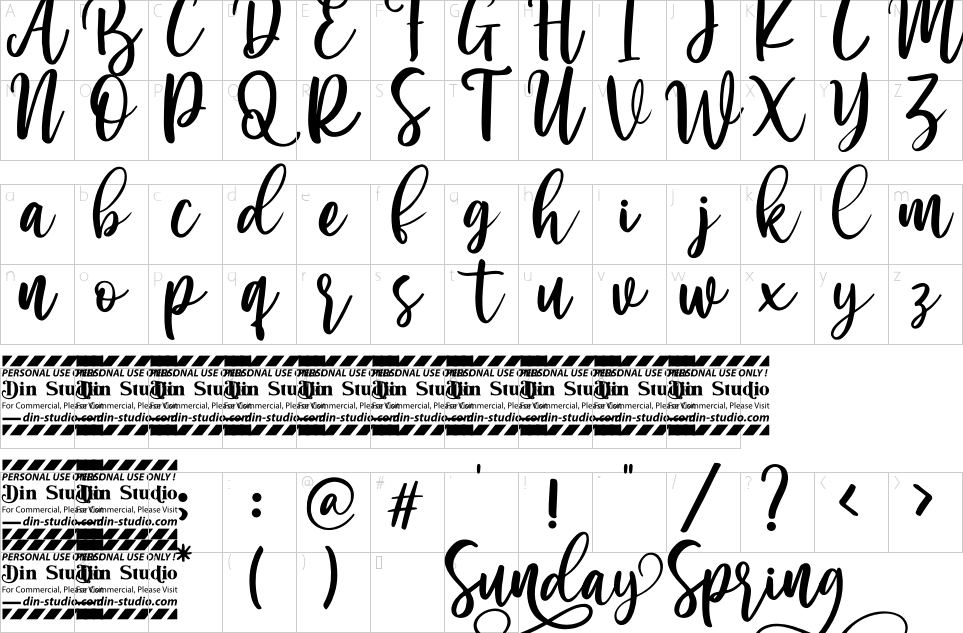
Sunday Spring Font – Download Grátis
Agora está disponível para download a Sunday Spring Font, uma elegante e versátil fonte que traz vida aos seus projetos digitais. Desenvolvida pelo Din Studio, esta fonte é ideal para quem procura um look moderno e envolvente para gráficos, editoriais de blog ou até mesmo para aplicativos. Com design minimalista e linhas leves, a Sunday Spring pode complementar diversos estilos de projetos. O download da font é fácil e rápido no Windows e Mac, com 7.934 pessoas já aproveitando esta oportunidade de personalizar seus textos com ela. Seja você um designer profissional ou um amante do design, não perca a chance de adicionar este recurso gráfico único ao seu portfólio ou projeto.